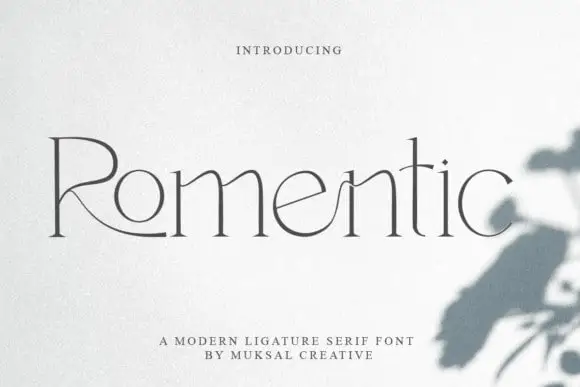
Romentic Serif Font – Download Grátis
A Romentic Serif Font é uma escolha perfeita para quem busca elegância moderna no design tipográfico. Fabricada pela Muksal Creative, ela traz ao seu projeto um estilo único, combinando elementos clássicos e futuristas de maneira atraente. O logotipo exibe traços românticos nas letras minúsculas com curvas suaves no final das colunas mais altas que fazem do design uma verdadeira peça de arte. Este font é perfeito para os estilos de design relacionados à moda e editorial, pois se destaca em sua apresentação tanto masculina quanto feminina. Sua completa versão inclui letras maiúsculas e minúsculas, números e pontuação, assim como suporte para as principais línguas europeias. Seja você um designer de branding fashion ou uma editora buscando adicionar personalidade a seus materiais, a Romentic Serif é o seu font perfeito.